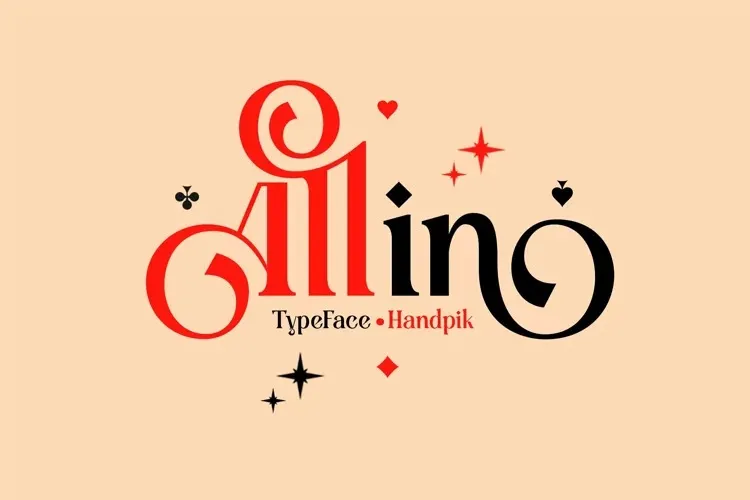
A fonte All In é uma elegante escolha para qualquer projeto que exige sofisticação e classe. Ela foi criada por handpik com um moderno toque, resultando numa aparência que deixa a impressão de riqueza e luxo. Com muitas ligaturas e alternativas disponíveis, ela se destaca especialmente em aplicações como cartões de convite, decorativos para festas, produtos vestimenta, cartas de cumprimentos, além de outros usos. All In é uma fonte completa com letras maiúsculas e minúsculas, números e pontuação. O seu conjunto multilingue também lhe permite adaptá-la a uma ampla gama de projetos internacionais. Esta fonte ainda inclui várias ligaturas e alternativas estilizadas que adicionam um toque único à sua identidade visual. Sem dúvida, é um excelente complemento para qualquer projeto que deseje transmitir sofisticação e elegância através da escrita.